九月,炎炎夏日渐逝,初秋的微凉扑面而来,恰如一幅色彩斑斓的画卷。在这个季节里,选择合适的字体能够更好地表达出九月的特点与情感。
首推宋体字,它如同九月的阳光,清爽明快,字形规整,端庄典雅。毫无疑问,宋体是表达文字内容的首选,其简洁而稳重的特点,恰如九月初秋的气息。
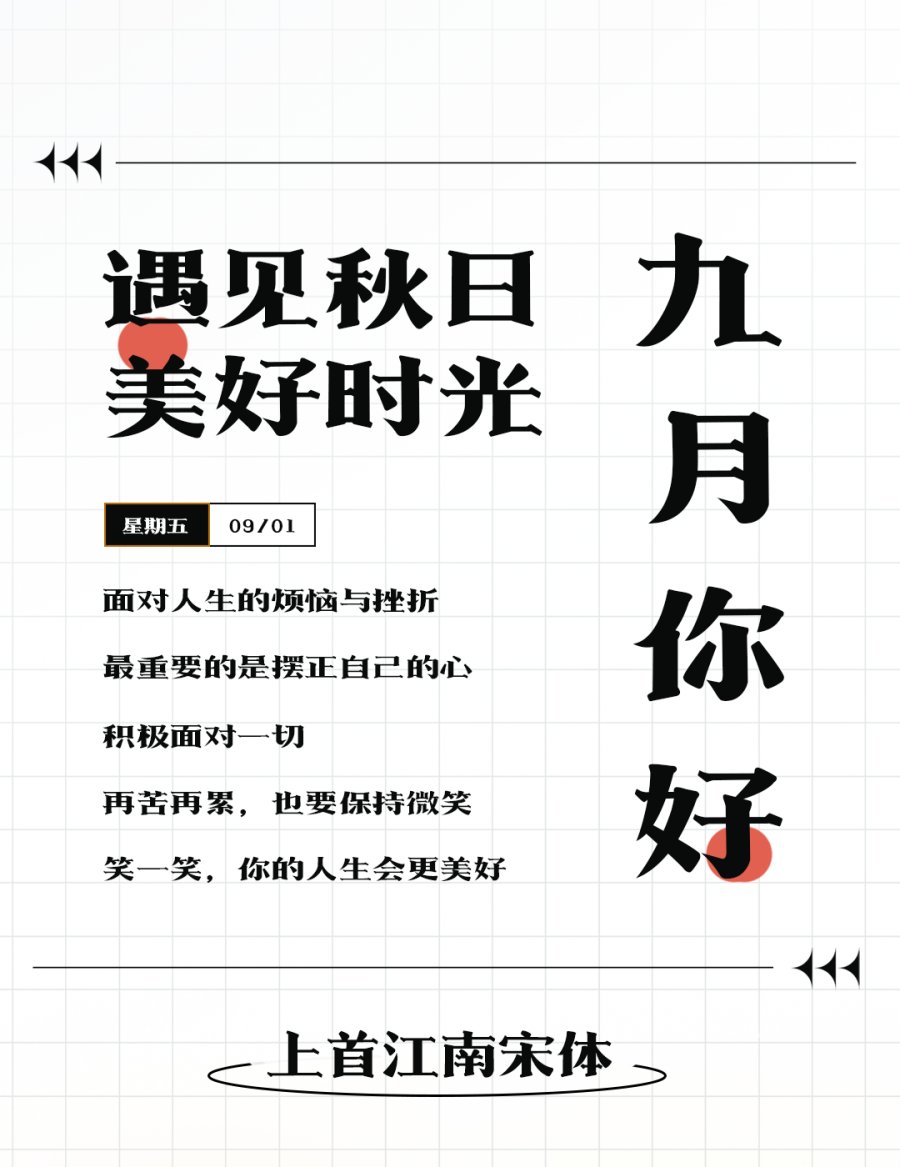
毛笔字,则像是九月的风,带着一丝自由与舒展。毛笔字的笔画流畅有力,蕴含着中国传统文化的独特韵味。它能够赋予文字以动感和生命力,如同九月中的微风轻拂着大地。
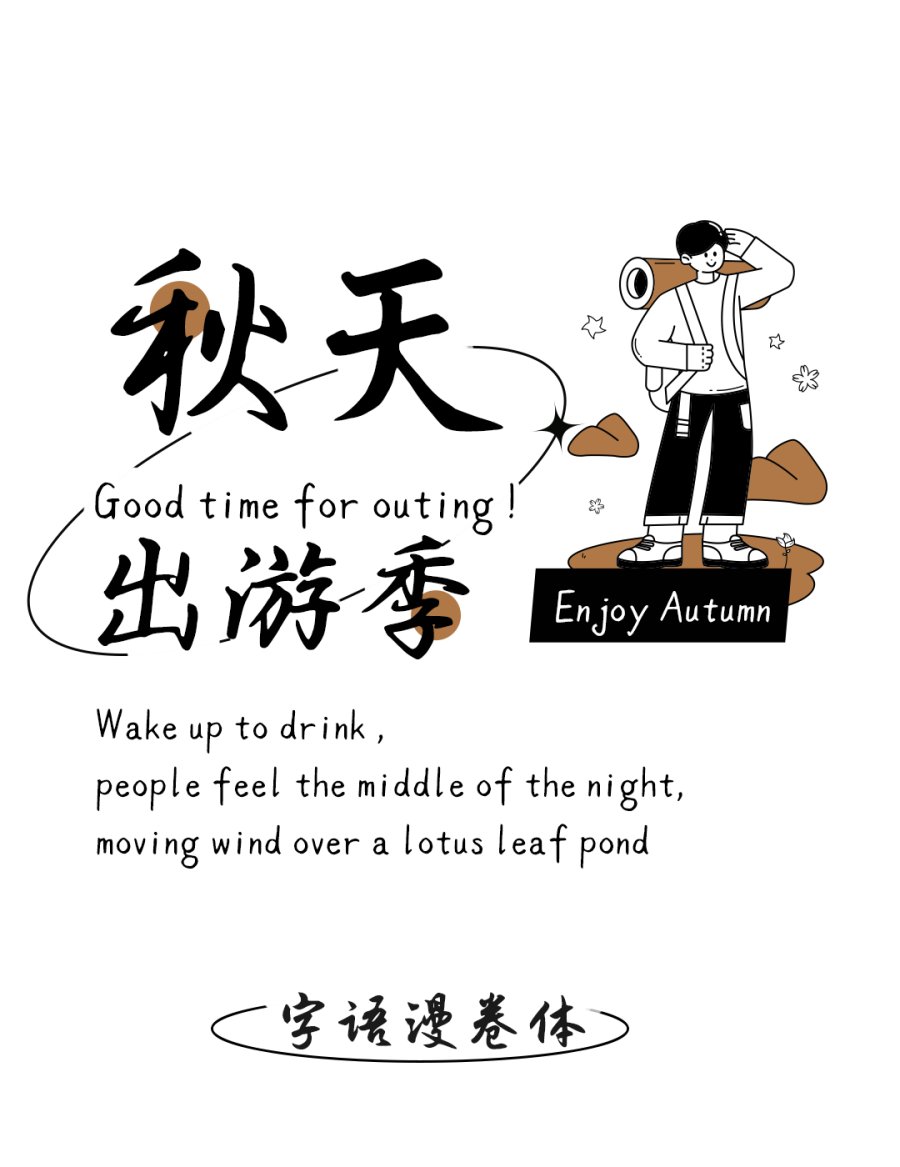
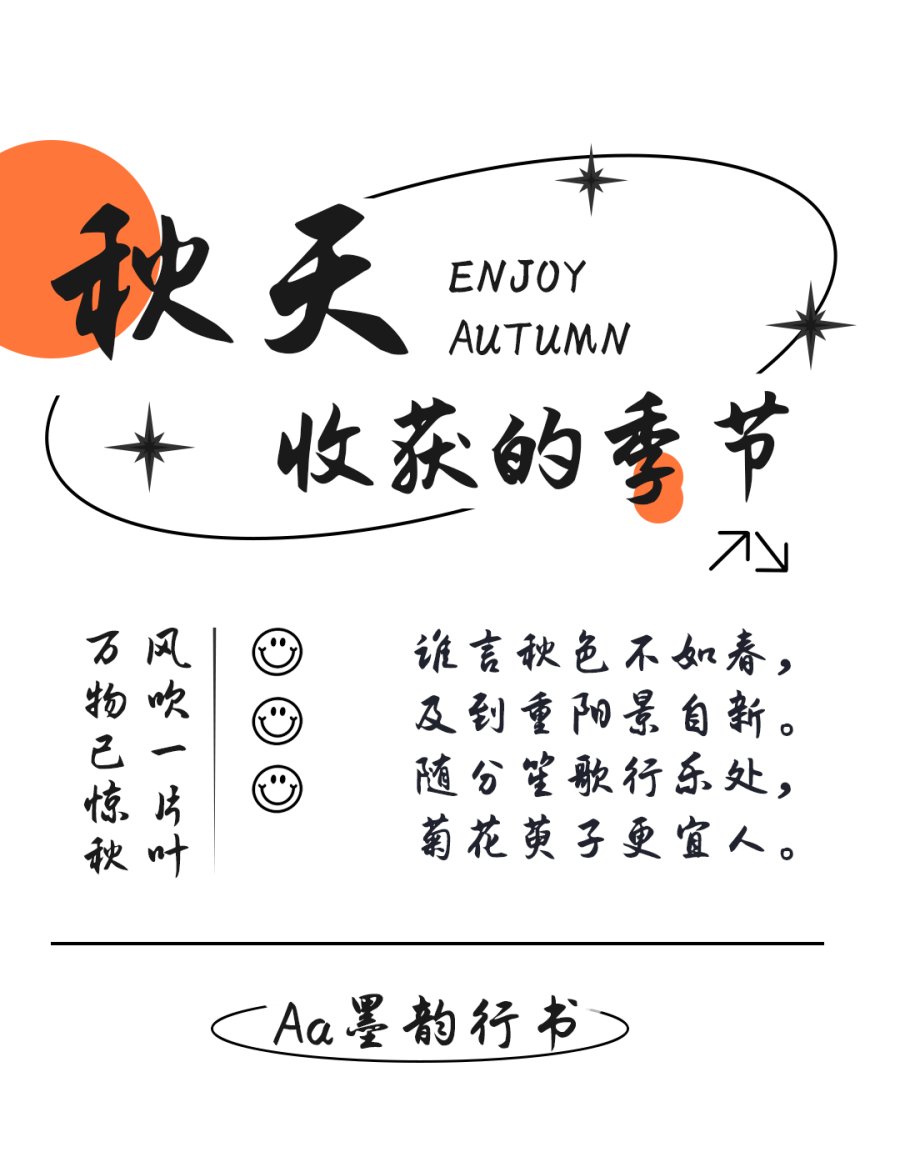
在设计领域,选择一款精美的设计字体能够为作品增色不少。一些现代感强烈的设计字体,如几何字体或艺术字体,能够为文字赋予时尚感和创意,仿佛是九月的夜晚,星空灿烂,充满未知和期待。
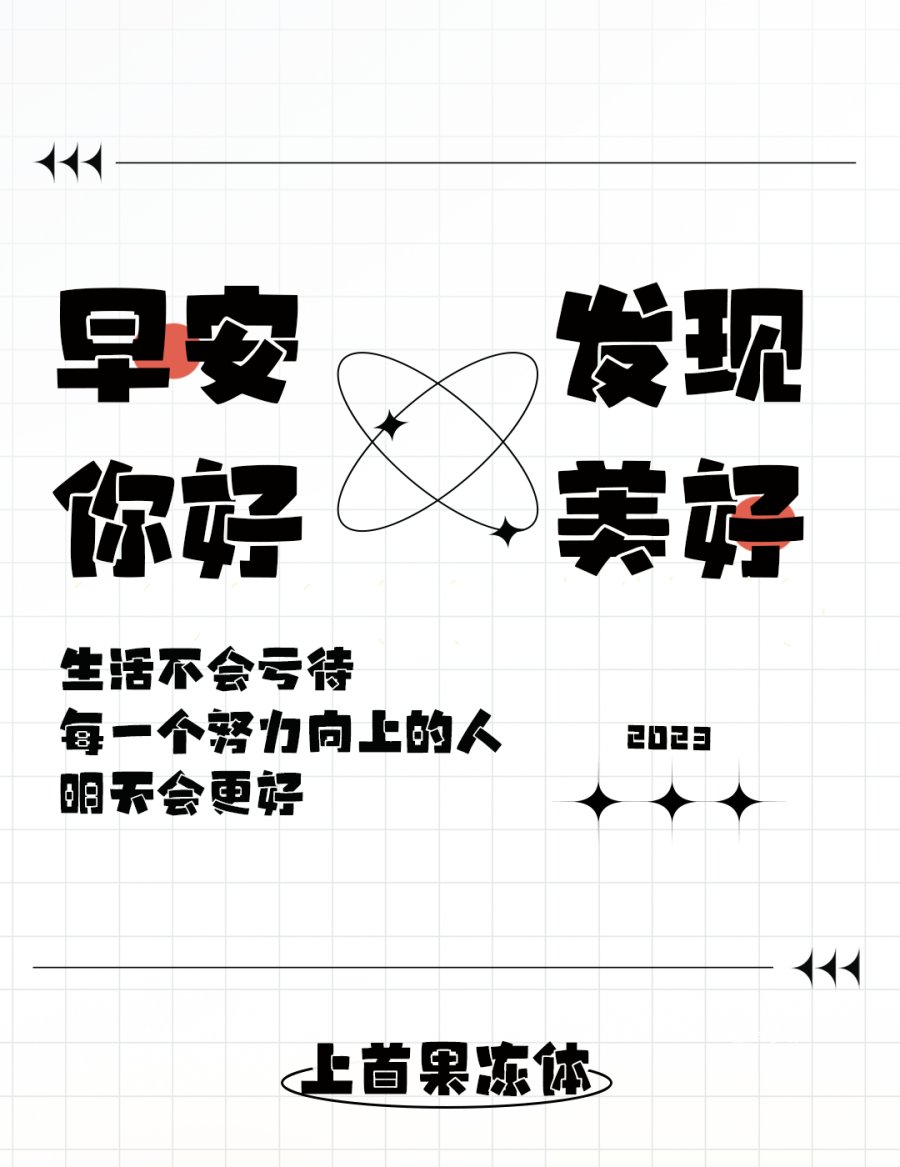
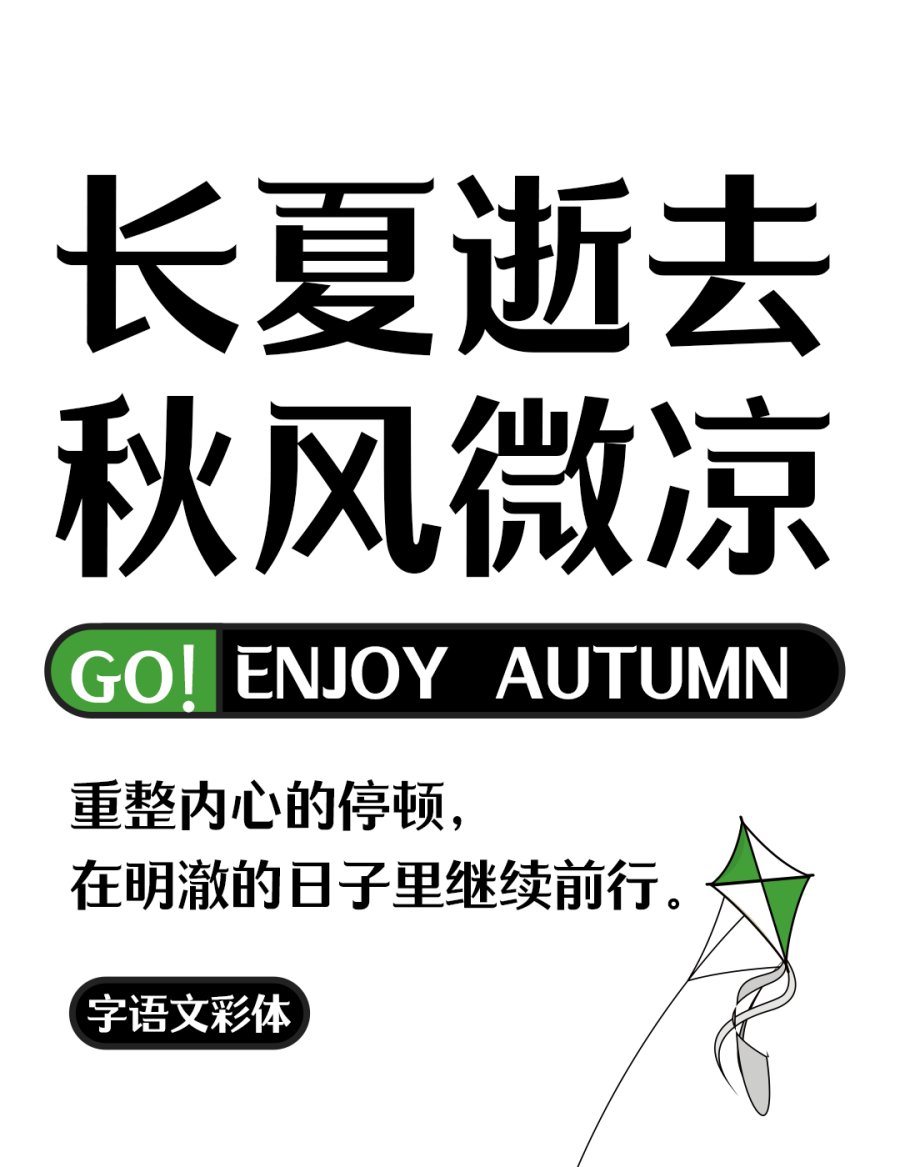
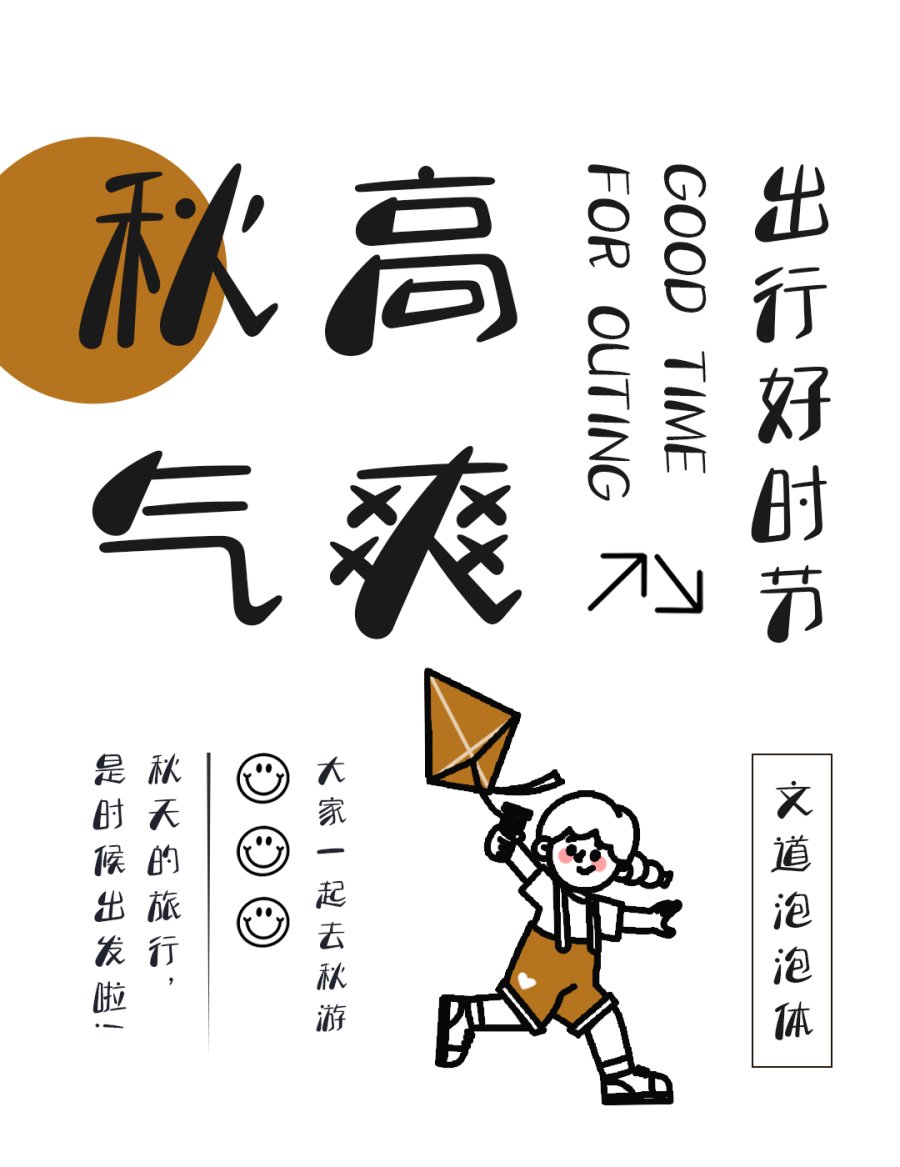
而手写字体,则像是九月的云,变化多端,充满个人特色。手写字体的独特性,能够为文字增添人情味和温暖感,如同九月的日子,时而炙热,时而凉爽,充满变化与惊喜。
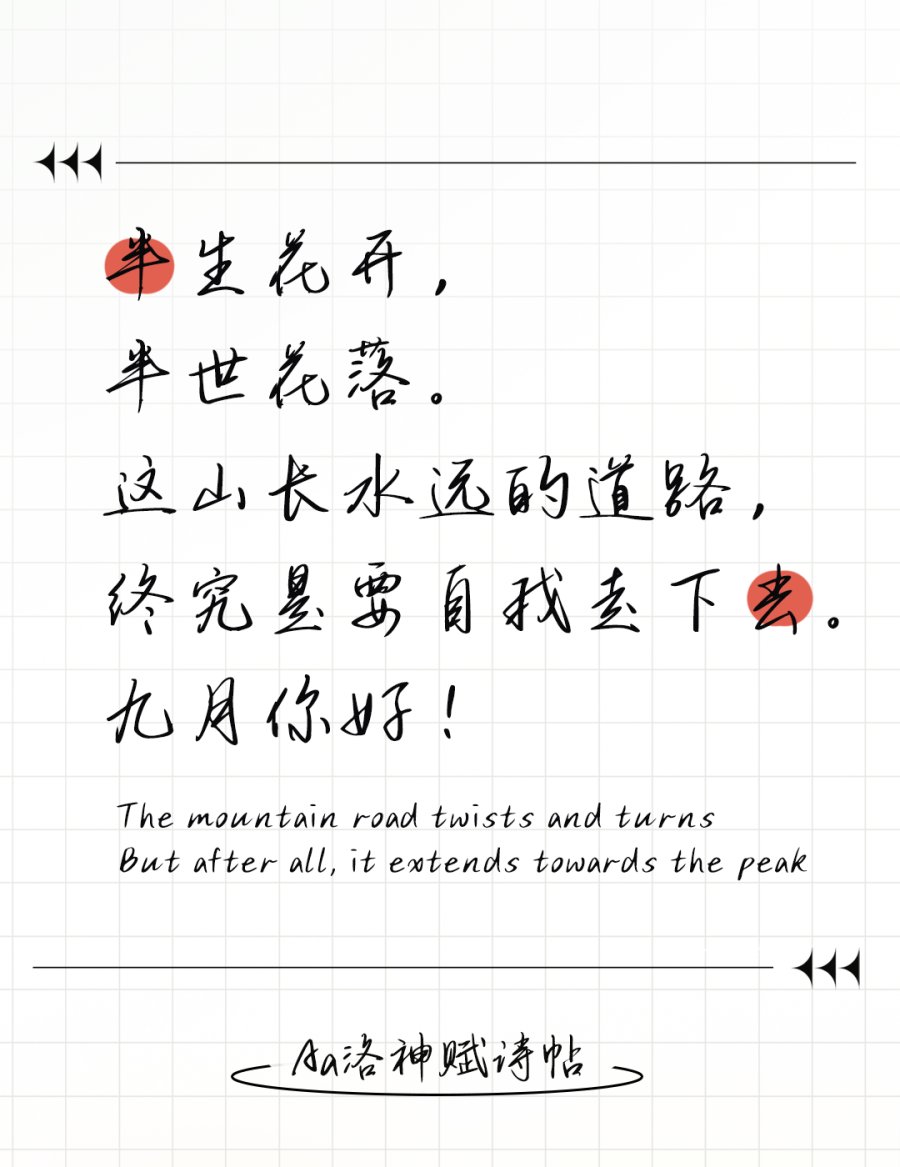
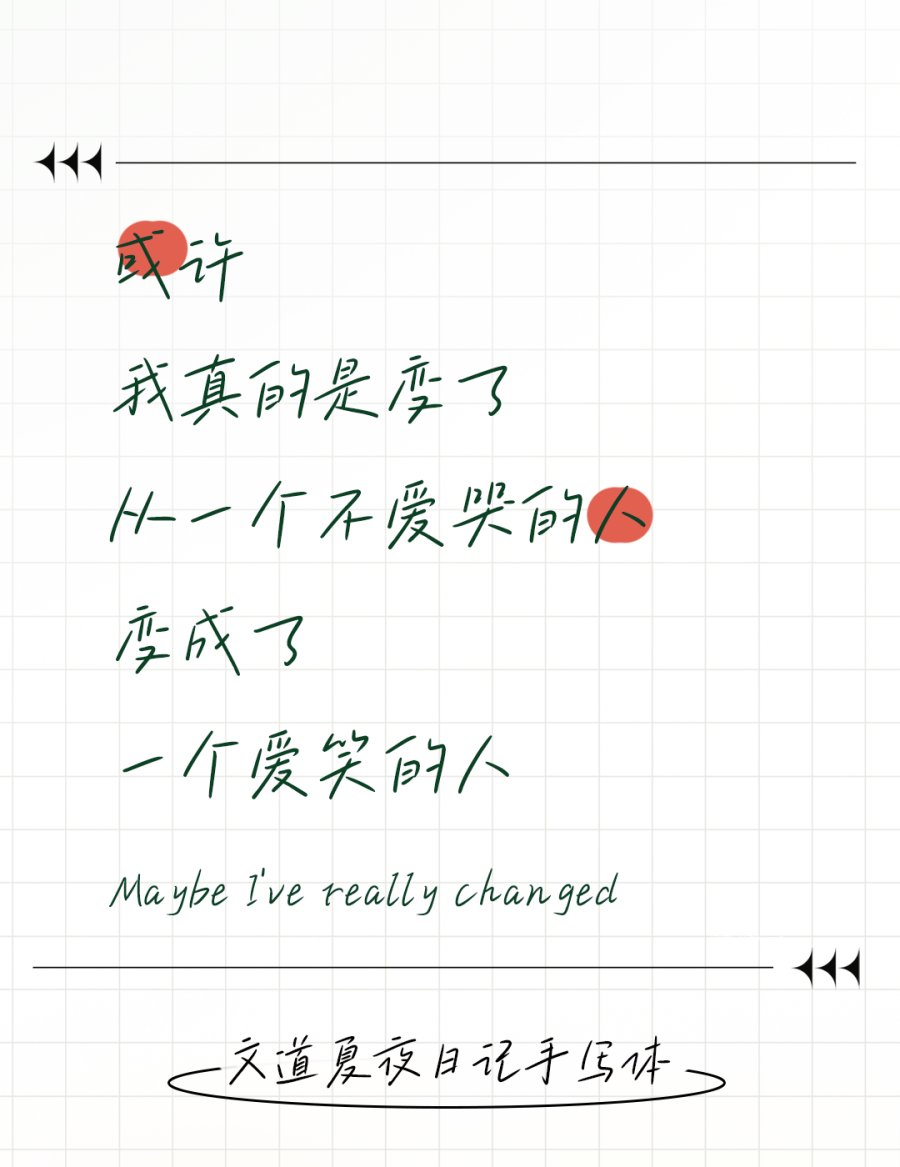
在这充满活力和变化的九月,选择适合的字体就像选择合适的心情一样重要。无论是传达信息,还是展现创意,合适的字体都能为文字赋予更丰富的内涵,让九月的故事更加精彩。